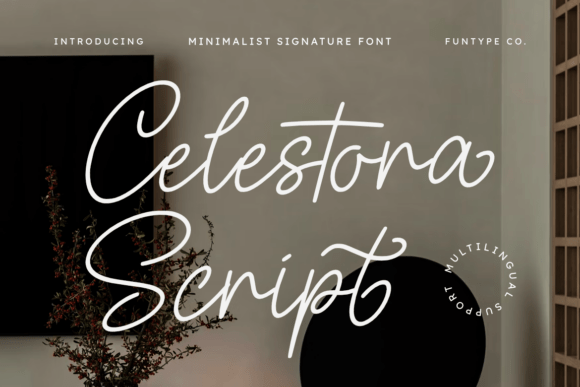
Celestora Script
Si buscas recursos de alta calidad como Celestora Script, este paquete premium es una opción fantástica para tus proyectos creativos.
Elaborado con precisión, Celestora Script proporciona vectores limpios, tipografía suave y una licencia comercial para tu tranquilidad.
Ya sea que estés creando productos POD (impresión bajo demanda), invitaciones de boda o gráficos para redes sociales, Celestora Script es una opción ideal.